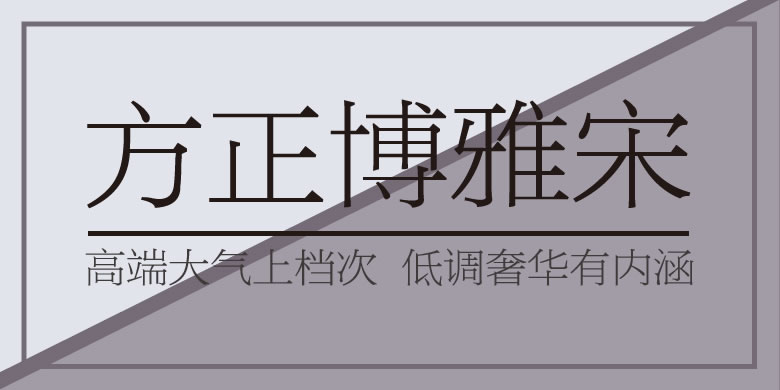
方正博雅宋
方正博雅宋,这款字体结构工整、笔画清晰,兼顾美观与易读性,适用于标题、正文、海报、包装、LOGO 等多种场景。字形优雅稳定,风格百搭耐看,适配日常排版与创意设计,让文字呈现更舒适、更具质感。方正博雅宋一笔一画,皆是细节,以均衡的比例、流畅的线条打造舒适视觉体验,字形端正大气,风格简约现代。无论是商业设计、品牌宣传还是日常排版,都能轻松驾驭,让文字更有格调与力量。方正博雅宋字体下载。
字体品牌: 方正字库 设计师:朱志伟 字体分类:宋体 字体属性:精品字 字符集:大陆简体(GB2312-80)、简繁扩展(GBK)、港台地区(BIG-5) 发布时间: 2004
方正博雅宋是一款专门针对报纸阅读而设计的新一代正文字体,其设计理念是“以人为本,关注读者视力健康”。方正博雅宋的字形扁方,中宫放松,字面大,横竖笔画粗细比例合理,横排视线流畅,适应长时间阅读。虽然它是一款正文字体,但由于结构宽博,线条简约坚固,还可用于标题。